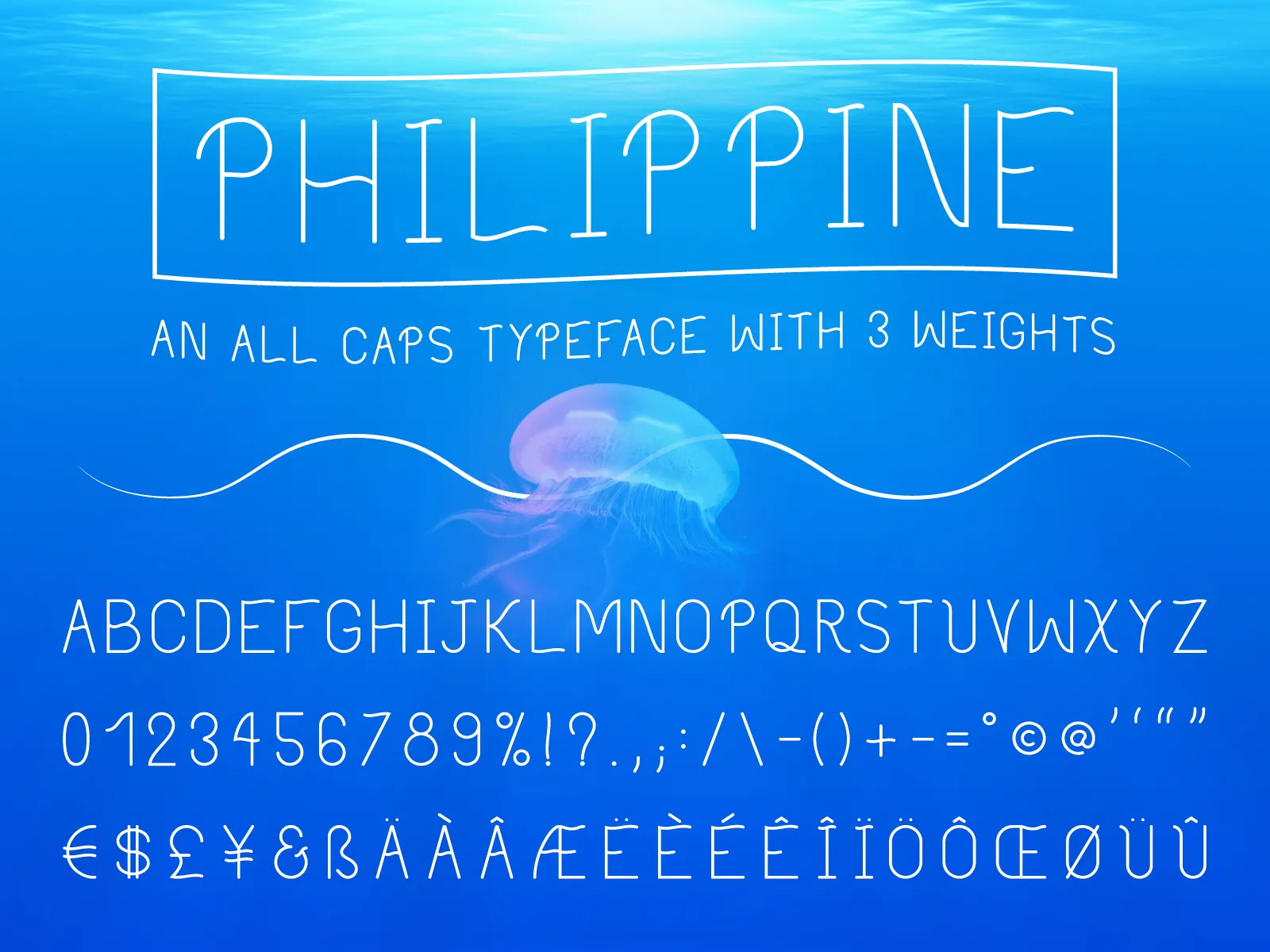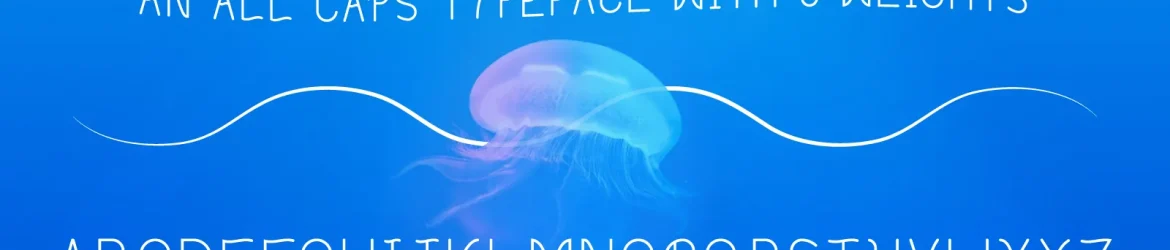
Aqui está uma descrição curta para a página de download da fonte ‘Philippine Font’, seguindo as instruções: Através do trabalho incansável de Valentin François, emergiu uma nova adição no universo das fuentes sans serif: ‘Philippine’. Esta all caps wavy font possui três pesos de negrito. Além disso, inclui acentos franceses e alemães. Ideal tanto para criações digitais quanto para aplicação em materiais impressos, essa fonte promete um toque único e moderno a seus trabalhos. Estamos emocionados por proporcionar esta font livre de royalties ao seu alcance. Seja pela sua utilização ou adaptação, este projeto é um marco inicial no trabalho do designer. Agradecemos desde já qualquer contribuição que você possa fazer para o crescimento da nossa comunidade criativa. E como acreditações são sempre apreciadas, teremos prazer em destacar seu trabalho na nossa plataforma.